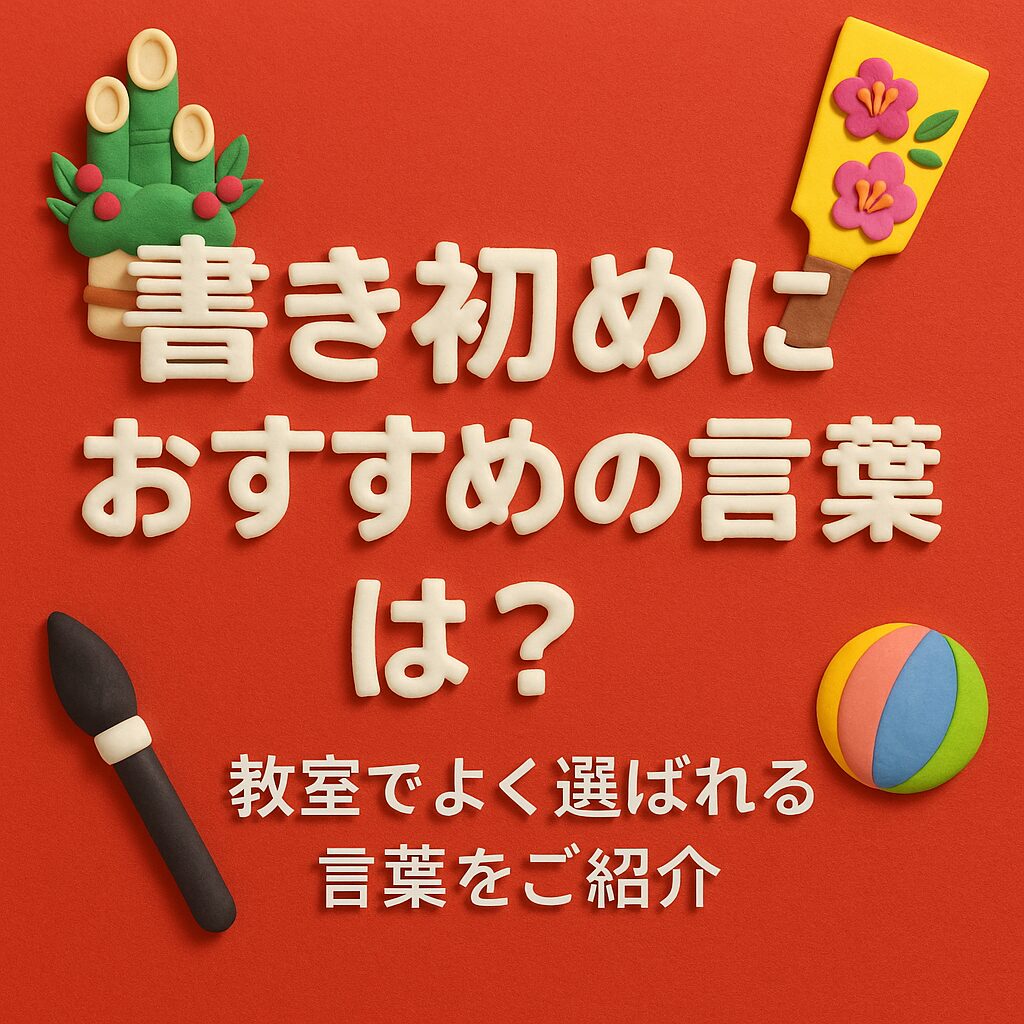
来年の1月2日も教室で「書き初め会」を開くことになりました。いつも練習している毛筆課題とはちがって、“新年らしい書き初め”として、子どもたちが自分の好きな言葉や今年の目標を書けるミニイベントです。冬休みは学校の書き初めの宿題でバタバタしがちですが、もじもじでは気楽にのびのび書ける時間にしたいと思っています。
自由に書けると言われると「何を書けばいいの?」と悩む子も多いので、もじもじでよく選ばれる言葉を分かりやすくまとめて紹介します。
◆【目標を言葉に】
挑戦
新しいことに向かう気持ちを書きやすい言葉。力強い線が出やすく達成感があります。
集中
気持ちを整えたい子によく選ばれます。スッと書くと全体が引き締まります。
努力
一年を通して意識しやすく親御さんにも人気。書くほど気持ちが前向きになります。
続
「続けたいこと」がある子にぴったり。形がシンプルで書きやすい字です。
◆【気持ちを言葉に】
笑
大きく書くと明るい雰囲気に。低学年でも書きやすい一字です。
優
“やさしくいたい”という子によく選ばれます。線にやわらかさが出ます。
嬉
書く本人の気分が明るくなりやすい字。バランスよく書けると達成感があります。
楽
「楽しい一年にしたい」と願う子に人気。読みやすく形も整えやすい字です。
穏
落ち着いた一年を過ごしたい子に。書いた後の紙の雰囲気がやさしくまとまります。
◆【好きな言葉を】
夢
毎年人気の一字。書きながら自然と目標を思い浮かべやすい言葉です。
感謝
家族への気持ちを書きたい子が選びがち。親御さんが喜ぶ一字です。
輝
線の動きが楽しく、書く姿もいきいきします。新年の雰囲気にもぴったりです。
【まとめ】
書き初め会は、子どもたちが“自分で言葉を選ぶ”特別な時間です。普段はお手本に合わせて書きますが、この日は気持ちや願いをそのまま筆に乗せるので、出来あがった紙を見るとその子らしさがよく伝わります。
「挑戦」「笑」「夢」など、子どもたちが自然に選ぶ言葉には、一年をどう過ごしたいかという小さな気持ちが込められています。親御さんには、ぜひ「どうしてこの言葉にしたの?」と聞いてみてください。そこには、日頃のがんばりや願いが隠れていることが多いです。
書き初めが、その子にとって一年のスタートを気持ちよく切れるきっかけになりますように。